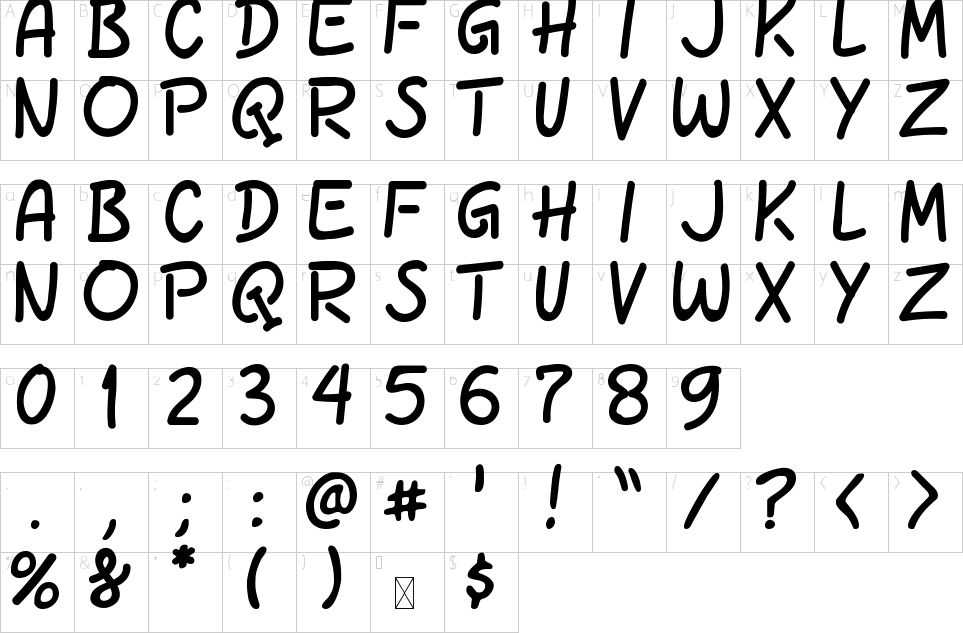
Milk Drink Font | 1001 Free Fonts – Fonte Grátis
Aqui está uma descrição em português do Brasil, envolvente e natural, para uma página de download da fonte ‘Milk Drink Font | 1001 Free Fonts’: A fonte ‘Milk Drink’ é um charminho de design que destaca-se entre as muitas opções gratuitas disponíveis na plataforma 1001 Free Fonts. Inspirada na simplicidade e bom gosto do leite e do café, esta fonte é perfeita para aqueles que buscam um touch diferenciado em seu próximo projeto. Com seus linhas elegantes e harmoniosas, a ‘Milk Drink Font’ garante um estilo único, seja ela usada em uma linda carta de apresentação, um slogan de marca atraente ou até mesmo na criação de um infográfico visualmente atraente. Se você está em busca de uma fonte que não apenas seja legal de se usar, mas também adere a sua personalidade e estilo, a ‘Milk Drink Font’ é uma escolha ótima. Que tal adicionar um pouco de doçura e sofisticação à sua próxima criação com essa fonte?
Mapa de caracteres da fonte Milk Drink Font | 1001 Free Fonts